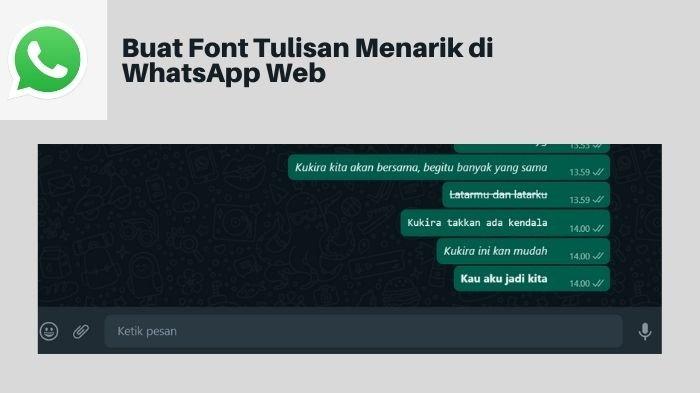
4 Font Tulisan WhatsApp Web yang Bisa Dicoba tanpa Aplikasi Tambahan, Bikin Chat Lebih Menarik!
Inilah cara buat font tulisan melalui WhatsApp Web, mudah dan bikin chat lebih menarik.
Tanpa aplikasi tambahan, begini cara memunculkan beberapa font tulisan di WhatsApp.
Tak hanya berlaku di WhatsApp Web, bikin font tulisan unik ini juga bisa dicoba di WhatsApp pada ponsel.
Beberapa pengguna tentu bosan dengan font tulisan WhatsApp yang begitu-begitu saja, ini solusinya.
Setidaknya ada 4 font tulisan yang bisa kamu gunakan agar membuat obrolan lebih menarik di WhatsApp, ikuti satu-satu ya!
1. Font tulisan miring
Ketik pesan di obrolan tertentu pada WhatsApp Web.
Sebelum dikirimkan, beri tanda baca garis bawah (_) di awal kata pesan dan di akhir pesan yang sudah ditulis.
Misalnya: _Ada apa?_
Setelahnya, kirim pesan tersebut. Otomatis pesan akan berubah menjadi tulisan miring.
2. Font tulisan dicoret tengah
Ketik pesan di obrolan tertentu pada WhatsApp Web.
Sebelum dikirimkan, beri tanda baca tilde (~) di awal kata pesan dan di akhir pesan yang sudah ditulis.
Misalnya: ~Ada apa?~
Setelahnya, kirim pesan tersebut. Otomatis pesan akan berubah menjadi coret tengah.